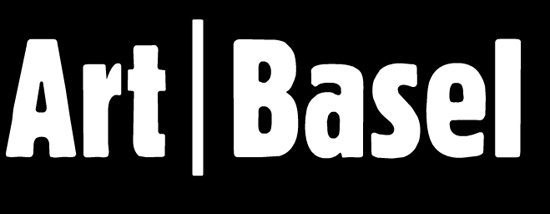
Welche Schriften? ART BASEL, UNI CREDIT BANCA; UPS ?????
Die Unicredit Schrift ist die wohl spannendste und meist gebrauchte neue Schrift. Sehr ähnlich ist die UPS-Font...
Die Art Basel Schrift ist einfach geil...
Wie heissen diese Schriftarten???